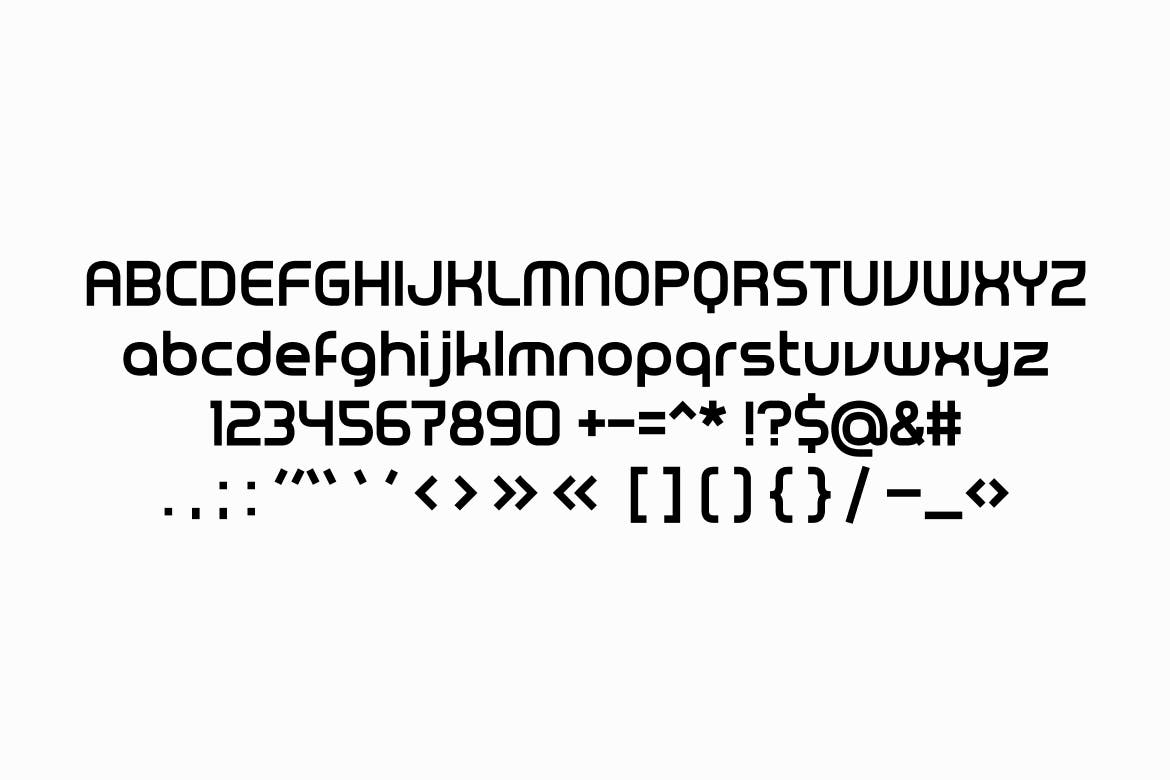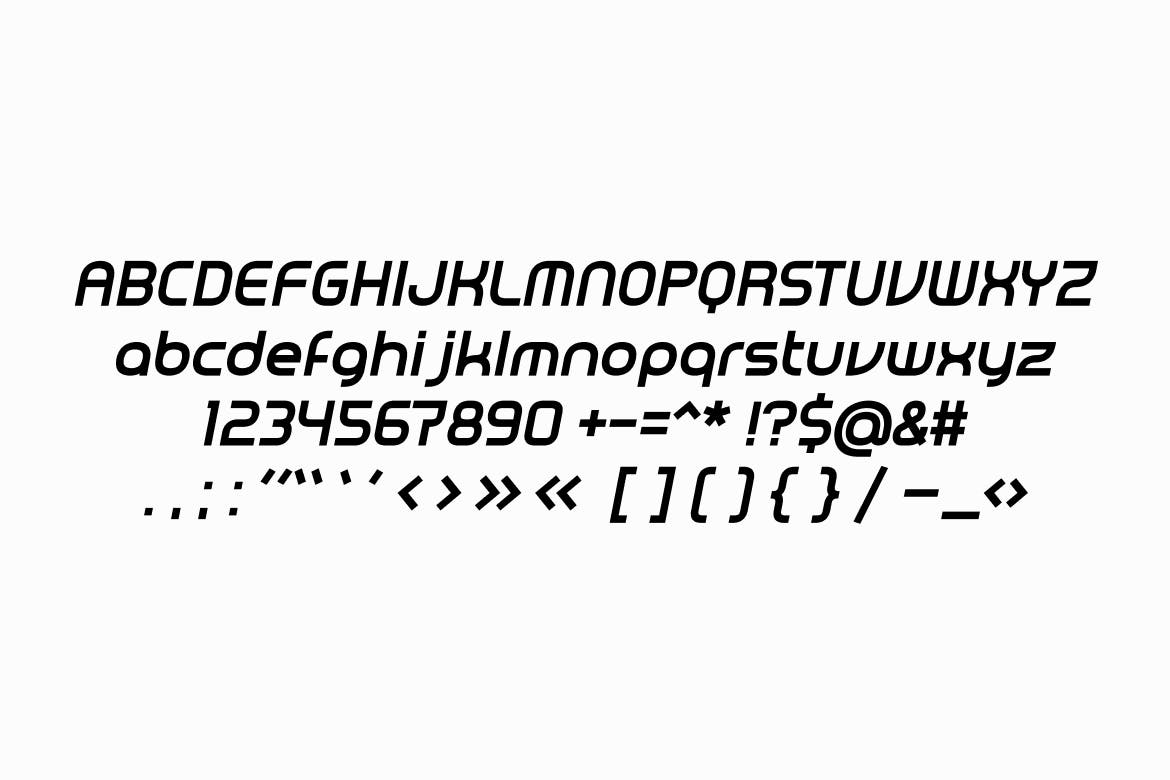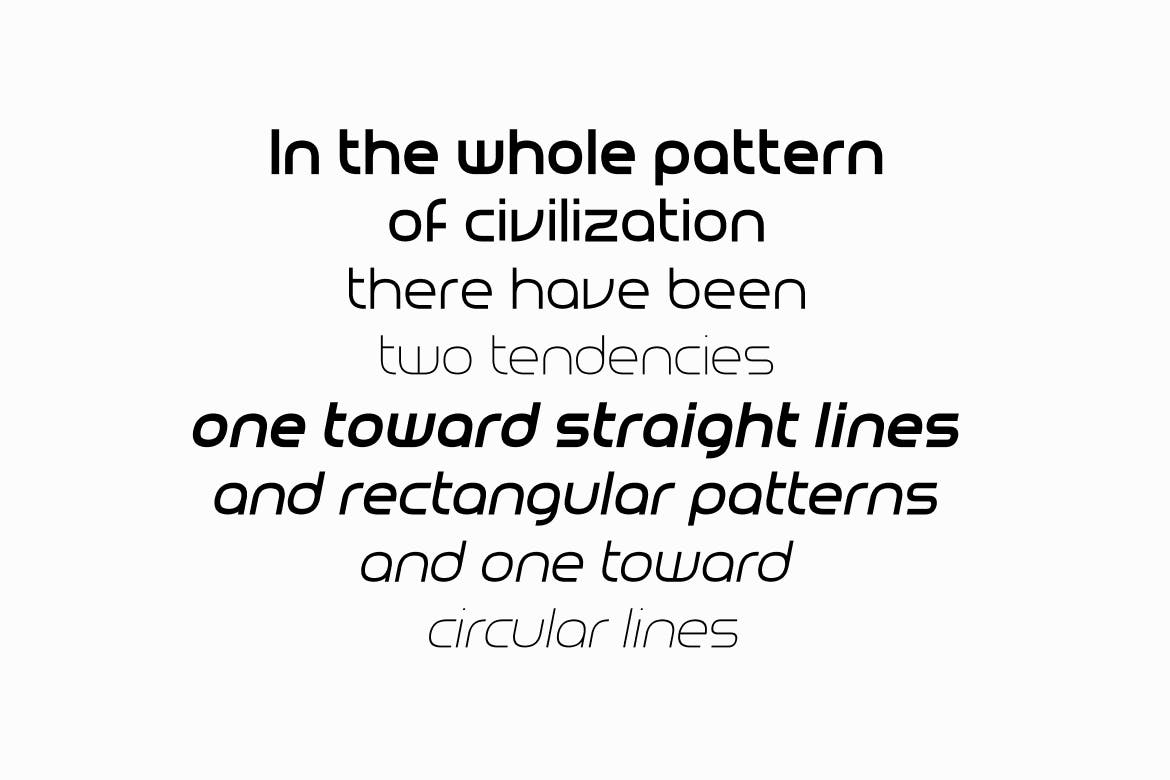
Elpi Modern Typeface
فونت Elpi با ۸ استایل مختلف، انتخابی مناسب برای طراحی‌های شما.
فونت Elpi - یک فونت مدرن زیبا و با دقت طراحی شده که دارای ۸ استایل مختلف برای پروژه‌های فوق‌العاده شماست.